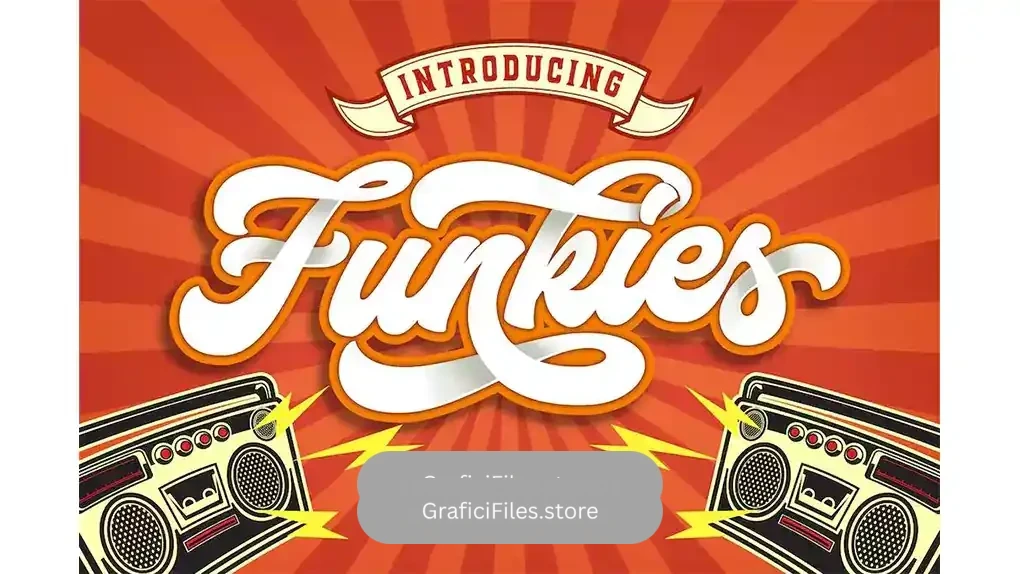
دانلود فونت انگلیسی دست نویس Funkies Bold Script Font
فونت انگلیسی دست نویس Funkies Bold Script Font : این مجموعه شامل یک فونت انگلیسی دست نویس کلاسیک است که برای لوگوتایپ، پوستر، جلد کتاب، طراحی تیشرت، بسته‌ بندی و غیره مناسب میباشد.
• فضا بین حروف: معمولی
• اندازه بهینه: تمامی سایز ها